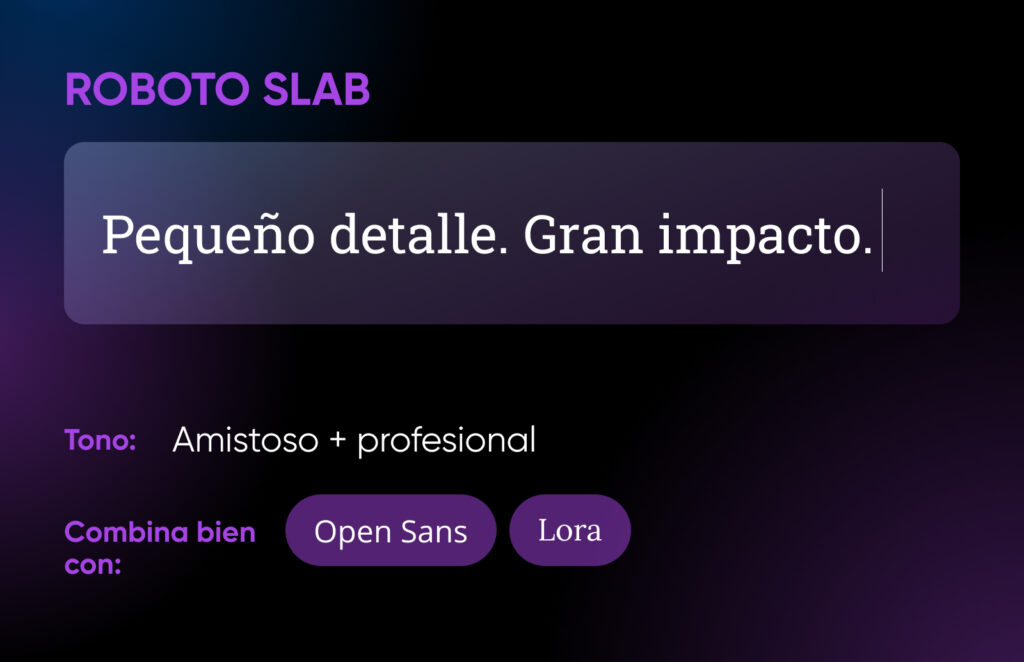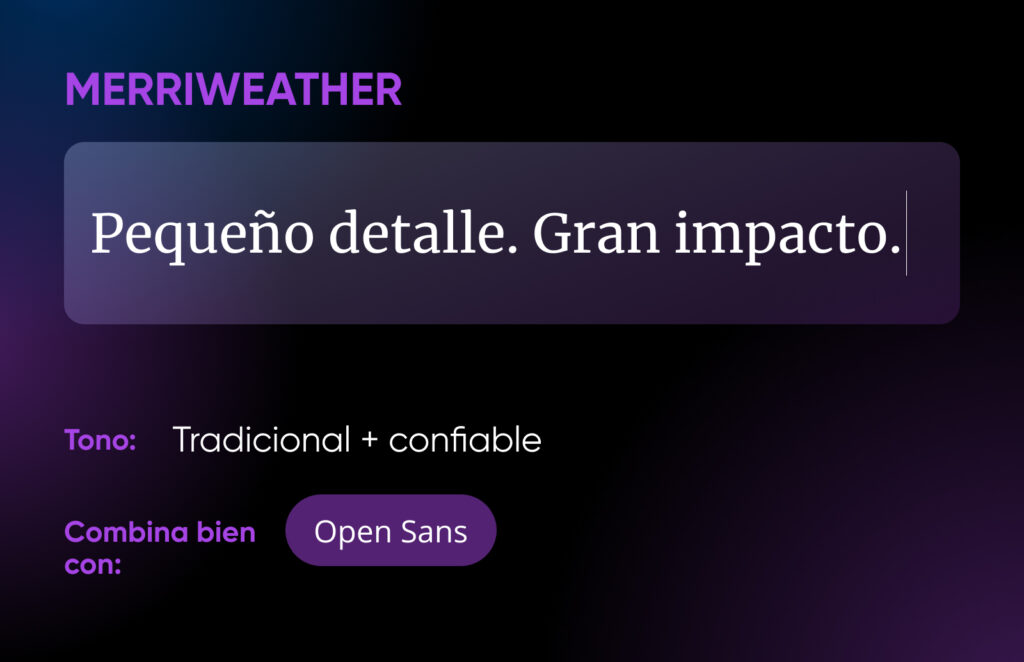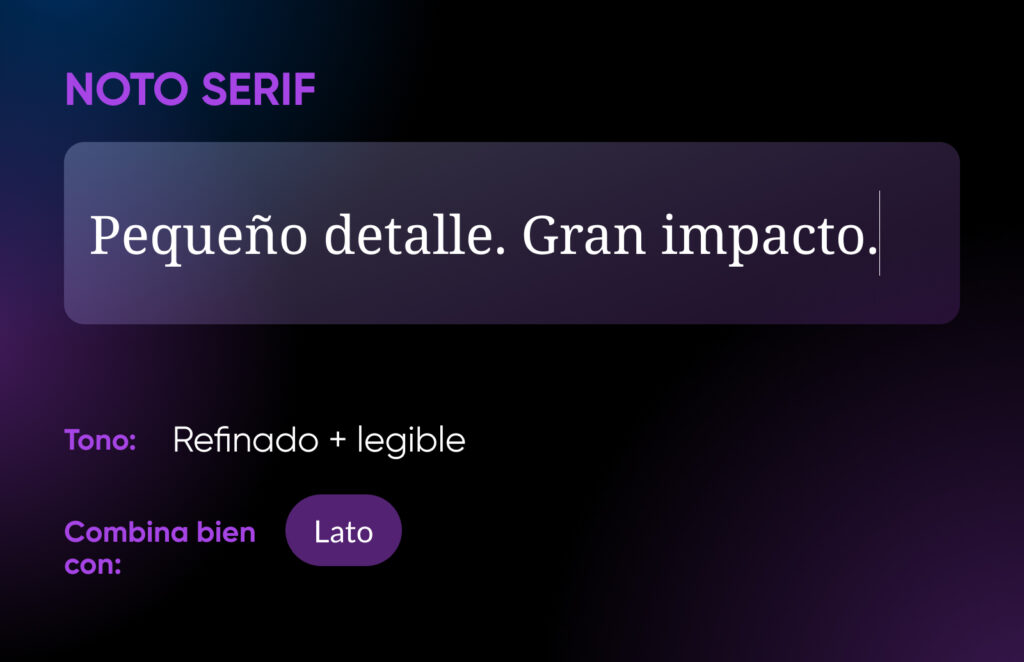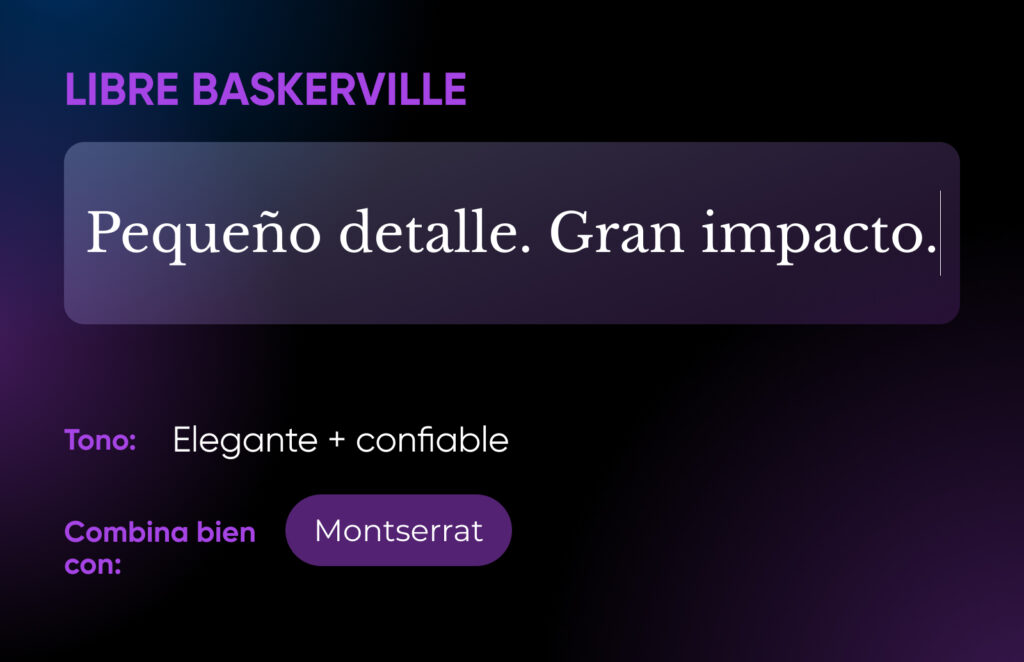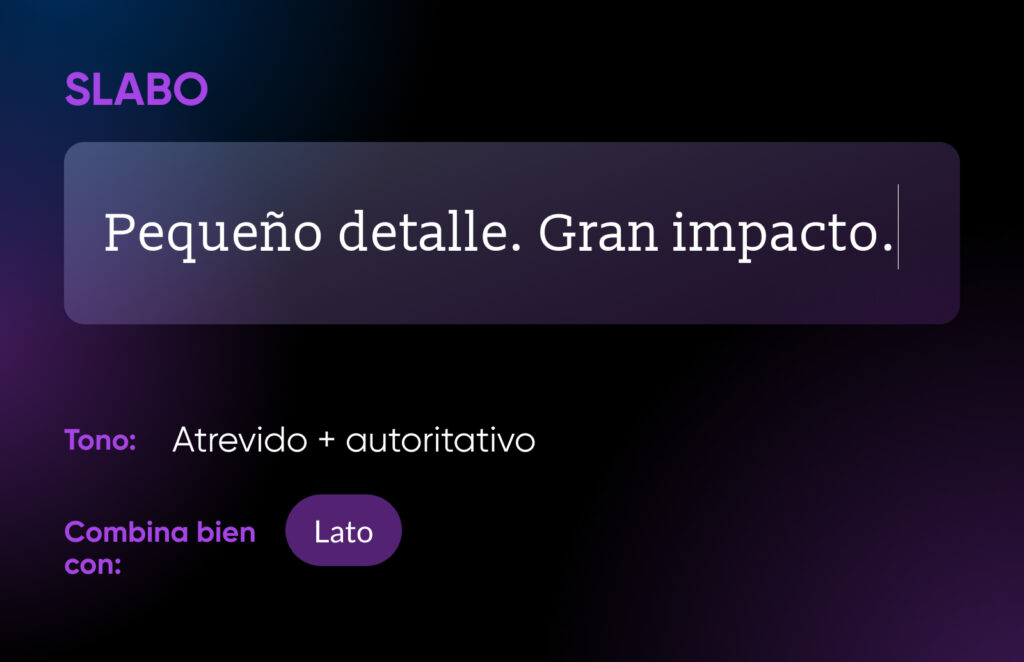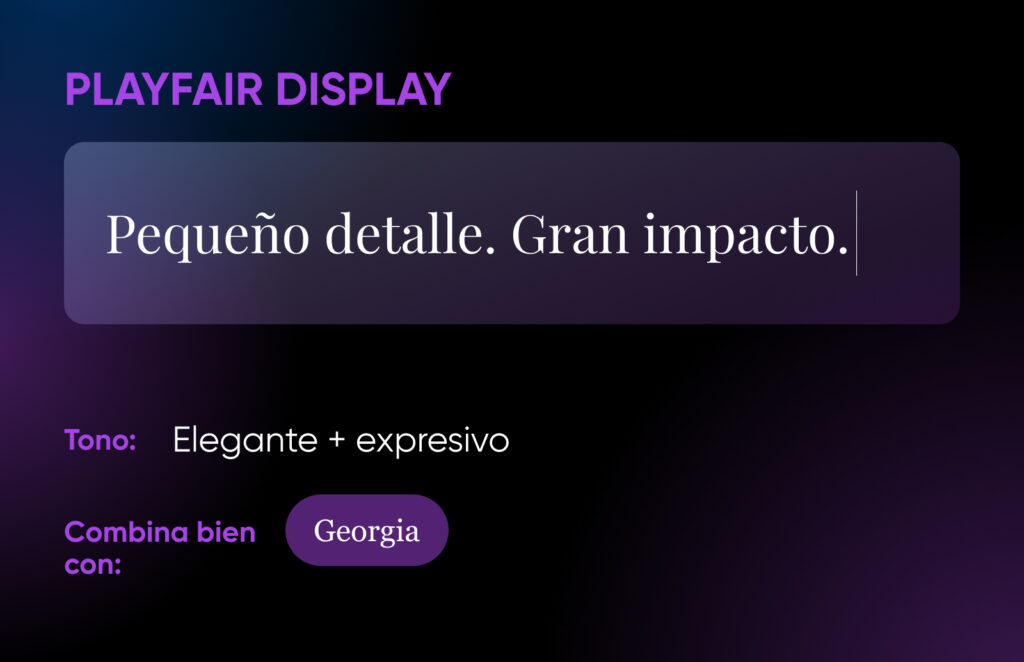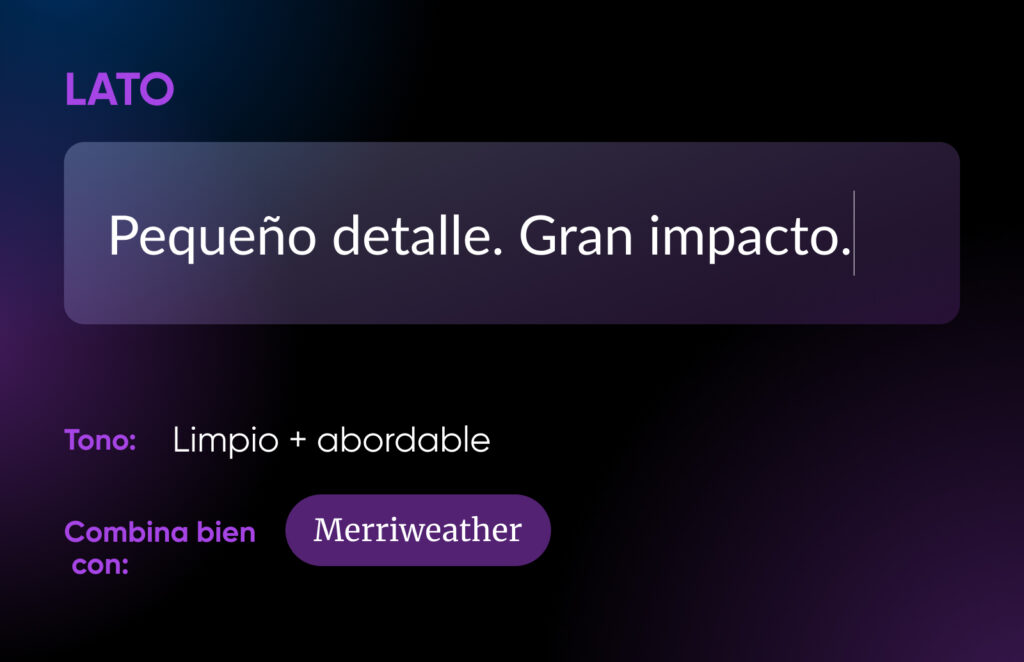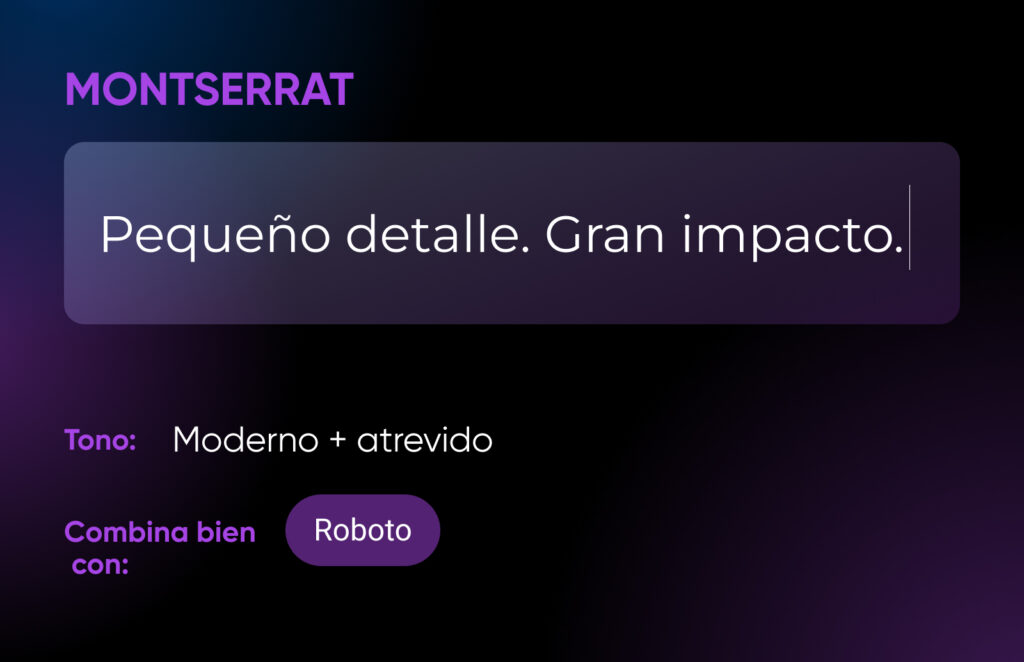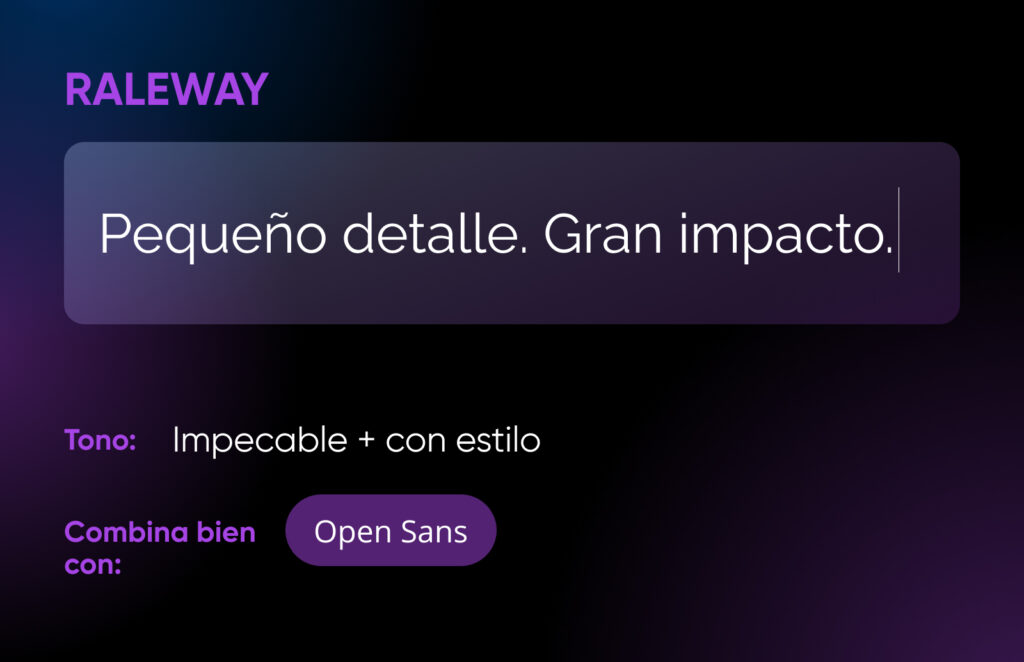
La tipografía es importante. Tu elección de fuentes tipográficas afecta tanto a la estética de tu sitio web como a la legibilidad de todo el contenido de texto. Hacerlo correctamente es vital si deseas ofrecer la mejor experiencia posible a los visitantes.
La parte complicada es encontrar la tipografía adecuada para tu marca. Con tantas opciones para elegir, puedes encontrarte luchando por ver el bosque entre los árboles. ¿Y cuál es la diferencia entre una fuente con serifas y una sin serifas?
La tipografía es el proceso de organizar un tipo de letra en variaciones de fuente, tamaño y espaciado. Esto implica hacer que la apariencia, el estilo y la disposición del texto sean legibles y agradables a la vista.Tipografía
Para ayudarte a orientarte en la dirección correcta, vamos a explorar 50 de las mejores fuentes de Google disponibles en este momento. Luego, veremos cómo crear combinaciones de fuentes perfectas y discutiremos las mejores prácticas para utilizar fuentes en tus diseños web.
Las 50 Mejores Fuentes Tipográficas de Google Para Tu Sitio
Ya sea que estés construyendo un blog sencillo o la próxima gran plataforma tecnológica, Google Fonts debería tener algo que se adapte a tu estilo. Aquí están las tipografías más destacadas en la vasta biblioteca, ordenadas por estilo:
Las Mejores Fuentes Serif
Las fuentes Serif muestran pequeños trazos (o “serifs”) al final de cada letra. Estas fuentes tipográficas tienen una apariencia bastante clásica y exudan un sentido de autoridad y tradición. Pueden comunicar confianza, lo que las hace ideales para periódicos, revistas y sitios de negocios serios.
Veamos algunas de las mejores fuentes de esta categoría.
1. Roboto Slab
Roboto Slab contiene curvas abiertas que permiten que las letras llenen tanto espacio como sea necesario. Puede proporcionar una experiencia al leerlas y se emparejan bien con muchas fuentes sans serif como Lato y Open Sans.
2. Merriweather
Merriweather fue diseñada para ser agradable de leer en pantallas. Presenta un leve estrés diagonal, lo que significa que las partes más delgadas de las letras están inclinadas para lograr una apariencia dinámica. Con su aspecto tradicional, Merriweather es perfecta para publicaciones literarias y sitios de noticias. Además, puedes combinarla fácilmente con Merriweather Sans.
3. Playfair Display
Influenciada por diseños del siglo XVII, esta tipografía se presta a sí misma para ese periodo. Playfair Display comunica un fuerte sentido de autoridad y sus letras en negrilla, bold, pueden hacer que tu texto resalte. Esta fuente combina bien con Georgia o su hermana Playfair Display SC.
4. Lora
Lora es una fuente contemporánea, bien balanceada con fuentes de caligrafía. Con sus curvas cepilladas y sus serifs redondeadas, Lora alcanza una apariencia única con un contraste moderado. Esto lo hace una excelente elección para los encabezados, así como también para texto de párrafos.
5. PT Serif
Dato curioso: PT Serif fue desarrollada para la “Tipografía Pública de la Federación Rusa”. Las letras parecen un poco alargadas y también bold y frescas. Como una fuente serif transicional con terminales humanísticas, es una gran pareja para PT Sans.
6. Noto Serif
Una mezcla de lo clásico y lo moderno, Noto Serif es conocida por su excelente legibilidad y un aspecto refinado adecuado para sitios profesionales. Gracias a sus formas de letras ligeramente condensadas, esta fuente funciona bien en espacios reducidos. Se combina bien con fuentes sans serif limpias como Lato y Open Sans.
7. Libre Baskerville
Libre Baskerville es una versión digital amigable de la clásica fuente Baskerville, famosa por su elegancia y legibilidad en impresiones. El estilo tradicional ha sido ajustado para una mayor claridad en pantallas, pero conserva mucha sofisticación. Combina esta fuente con Montserrat o Lora para una acción serif en serif.
8. Old Standard TT
Si buscas sofisticación atemporal, prueba Old Standard TT. Esta fuente recuerda a las tipografías utilizadas en publicaciones impresas a finales del siglo XIX y principios del siglo XX. Funciona especialmente bien para encabezados y para texto principal donde deseas un tono tradicional y formal. Combina bien con Lato.
9. Vollkorn
En alemán, Vollkorn significa “grano entero”. La fuente cumple con esta descripción, con un aspecto orgánico y saludable. Invita a los visitantes a leer tu contenido junto al fuego con una taza de cacao. Por lo tanto, Vollkorn funciona mejor para sitios relacionados con manualidades, comida o naturaleza. Combínala con fuentes sans serif neutras, como Source Sans.
10. Slabo
Creada específicamente para proyectos web, Slabo se adapta a cualquier densidad de píxeles. Esto significa que se ve igual de nítida en pantallas Retina que en antiguas pantallas de PC. Su aspecto general es elegante y profesional, lo que la convierte en una buena elección para sitios de negocios y comercio electrónico.